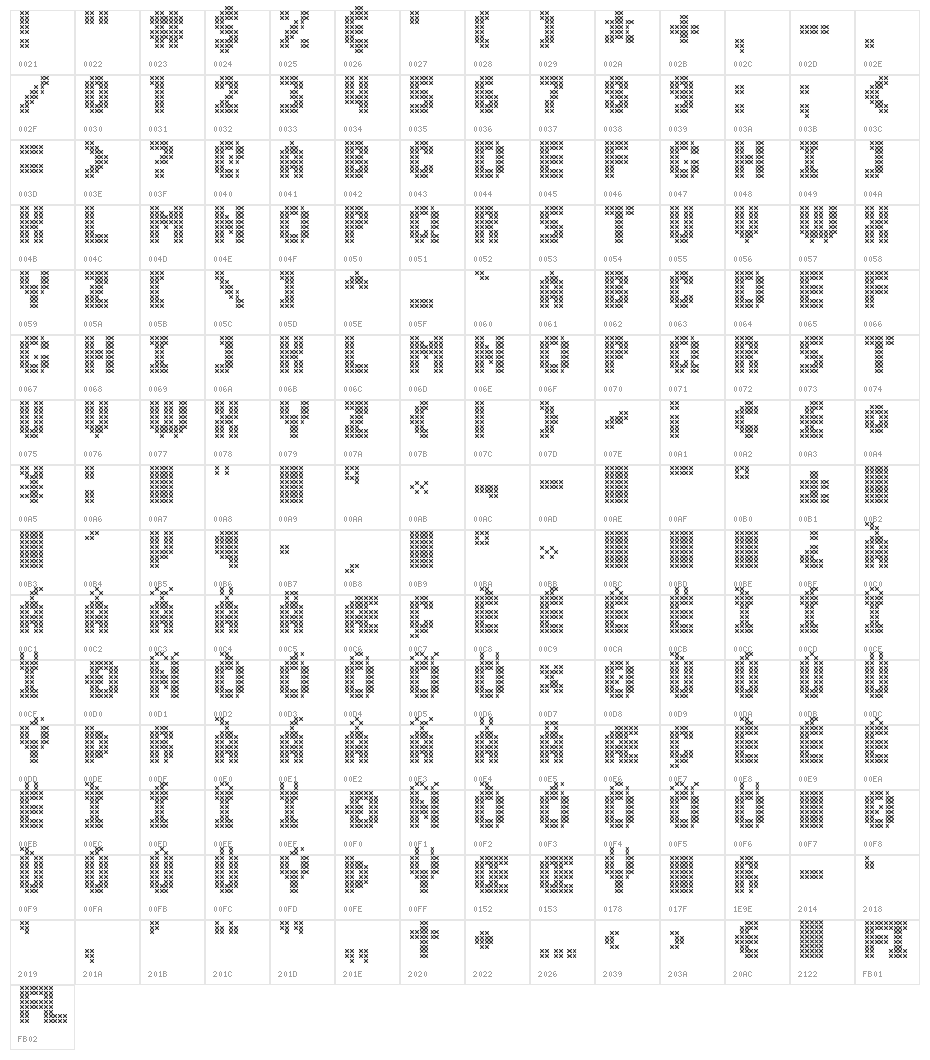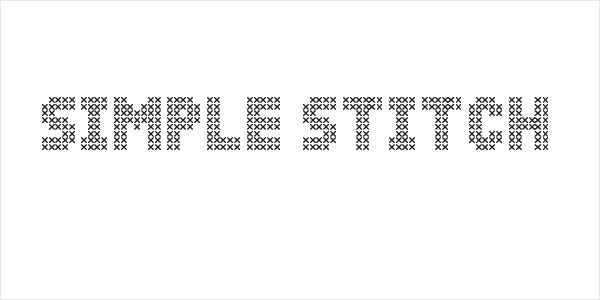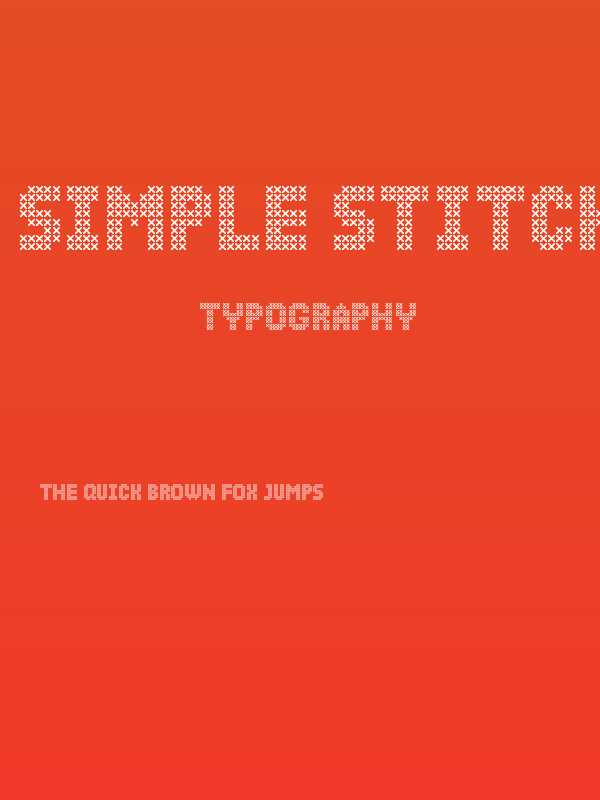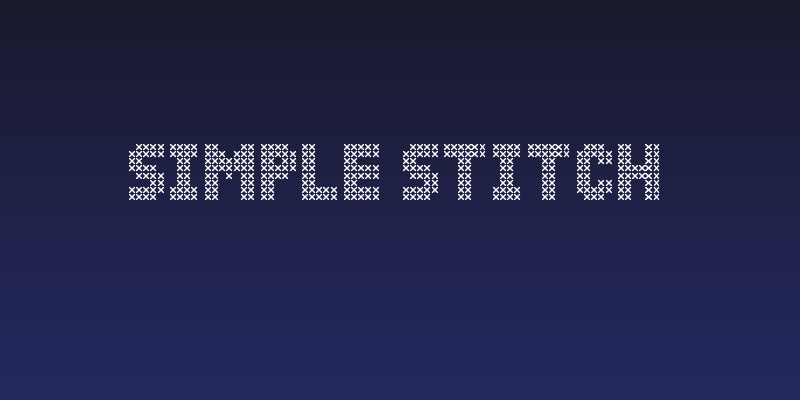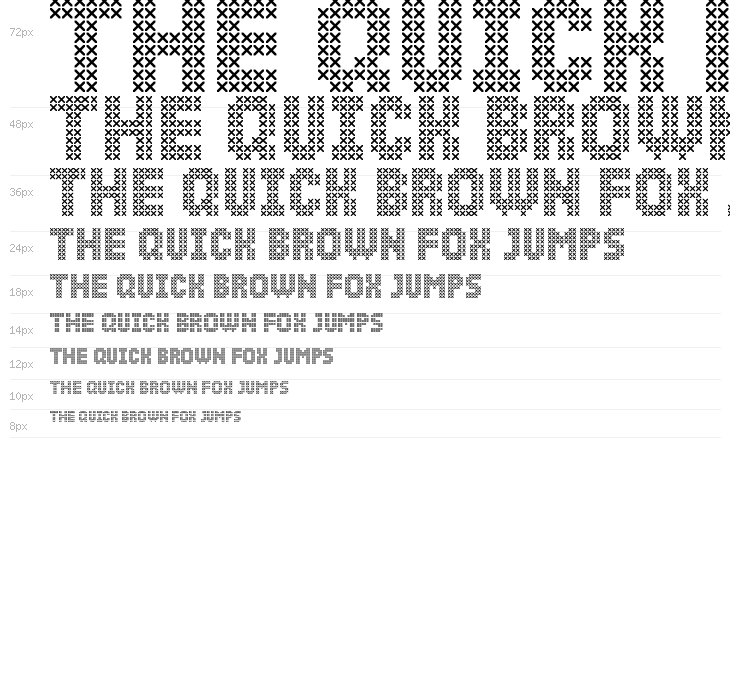
Simple Stitch Font
| Cas d'utilisation | Logos, Headlines, Craft projects |
| Projets proposés | Perfect for craft-themed designs, DIY projects, personalized gifts, and creative branding. |